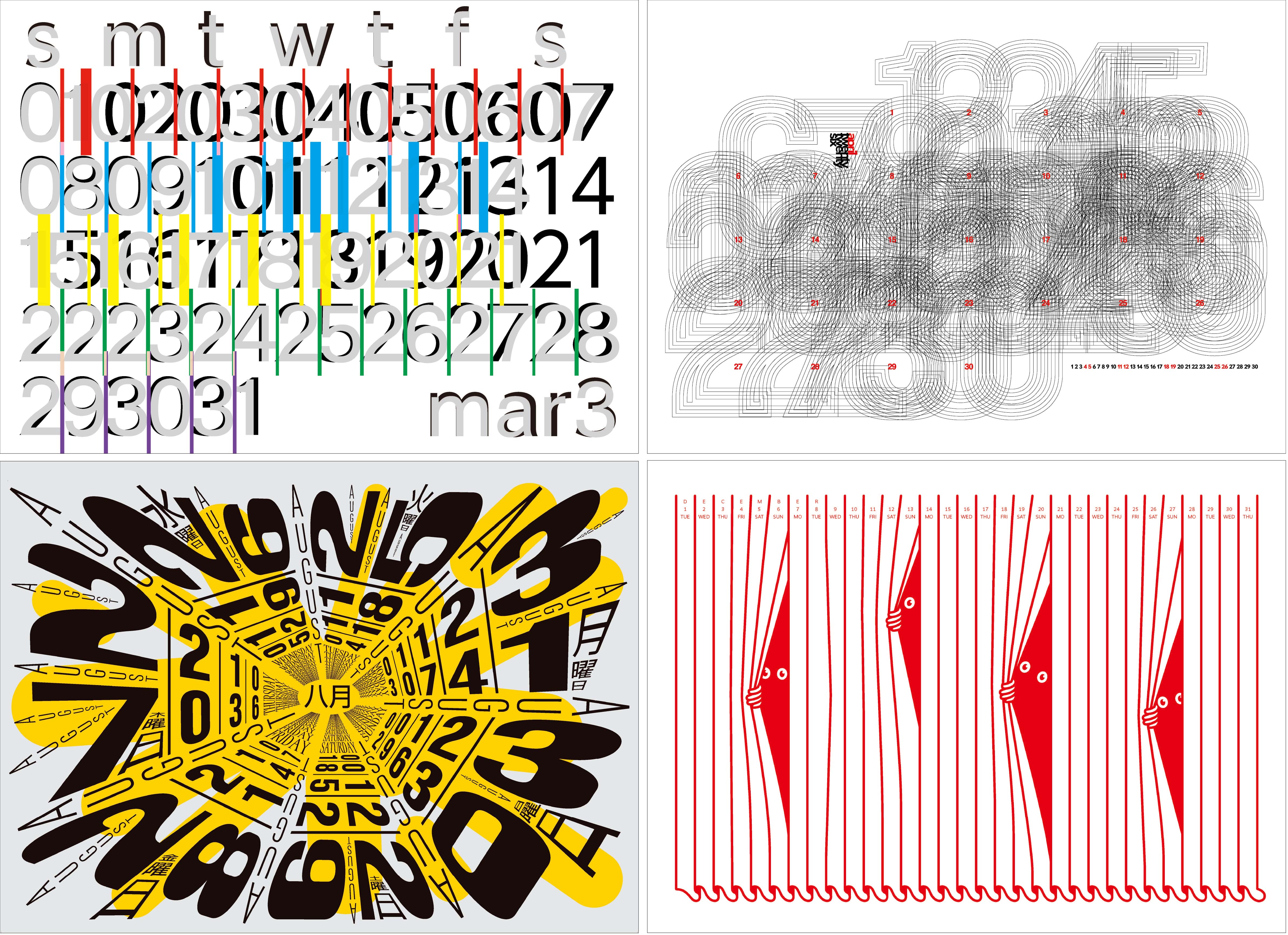
モリサワ 2026年カレンダーが、第77回全国カレンダー展で第1部門 経済産業省大臣官房商務・サービス審議官賞、金賞を受賞
株式会社モリサワの2026年カレンダー「Kerning(カーニング)」が、第77回全国カレンダー展で第1部門 経済産業省大臣官房商務・サービス審議官賞、金賞を受賞しました。
今回の受賞作品は、豊富な多言語書体を提供しているモリサワが、欧文書体用語でもある「Kerning(文字の間隔や余白の間)」をテーマに、世界各地から12名のデザイナーを招き、それぞれに一年を彩る一枚を託しました。彼らは、文字と文字のあいだのみならず、国や文化、人と人、物と物の間に潜む“間”を独自の視点で解釈し、意匠として表現しています。異なる文化や感性が重なり合うことで生まれるリズムや余白の意味が、一枚ごとに異なる響きをもち、日常に新たな気づきや対話をもたらすことを願って制作したものです。